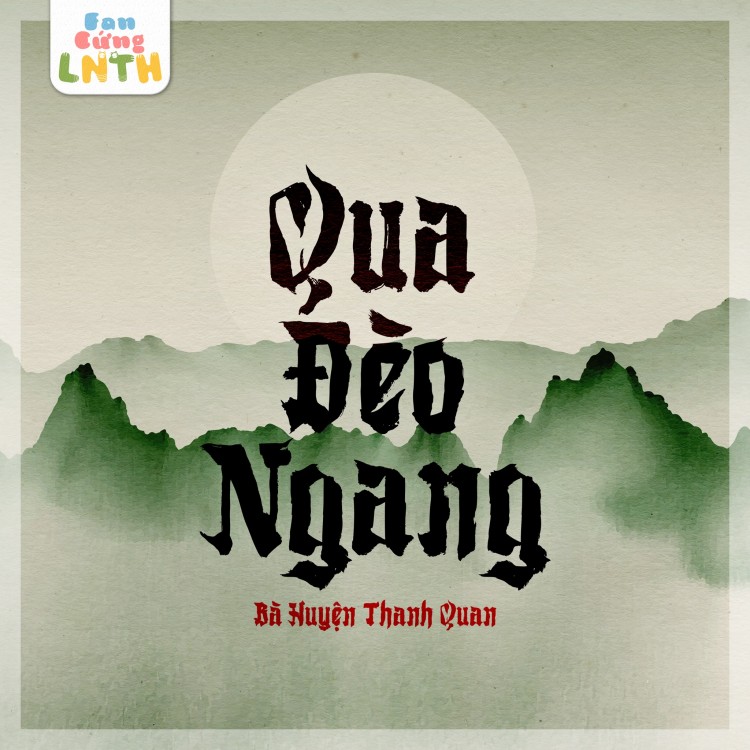
Font việt hóa LNTH Shodo Gothic – Sự kết hợp hoàn mỹ giữa thư pháp và hiện đại
Giới thiệu về Font việt hóa LNTH Shodo Gothic
Trong thế giới thiết kế đồ họa, việc lựa chọn một Font Chữ phù hợp đóng vai trò quyết định đến linh hồn của tác phẩm. Font việt hóa LNTH Shodo Gothic là một sự lựa chọn phá cách, mang đến vẻ đẹp độc đáo khi kết hợp tinh hoa của thư pháp Nhật Bản (Shodo) với cấu trúc hiện đại của phong cách Gothic. Bộ font này không chỉ giữ được những đường nét mạnh mẽ, dứt khoát mà còn đảm bảo tính thẩm mỹ cao cho người dùng Việt Nam. Nhờ quá trình việt hóa chỉn chu, các dấu câu và ký tự đặc biệt được xử lý khéo léo, giúp các bạn học sinh và thầy cô dễ dàng ứng dụng vào các dự án học tập hay trang trí bảng tin trường lớp một cách chuyên nghiệp nhất.
Đặc điểm nổi bật của bộ font LNTH Shodo Gothic
Phong cách thiết kế độc bản
Font việt hóa LNTH Shodo Gothic gây ấn tượng bởi những nét cọ mô phỏng bút lông truyền thống nhưng lại có khung xương chữ vững chãi. Sự tương phản giữa nét thanh và nét đậm tạo nên nhịp điệu thị giác lôi cuốn, phù hợp cho các tiêu đề sách, bìa báo cáo hay các mẫu slide thuyết trình cần sự trang trọng nhưng vẫn đầy tính nghệ thuật. Bộ font này giúp truyền tải thông điệp một cách mạnh mẽ và giàu cảm xúc.
Tính ứng dụng thực tế cao
Dù mang hơi hướng nghệ thuật, Font việt hóa LNTH Shodo Gothic vẫn duy trì được độ dễ đọc cần thiết. Đây là ưu điểm lớn giúp nó trở thành công cụ hỗ trợ đắc lực cho việc thiết kế poster sự kiện trường học, thiệp mời hoặc làm nổi bật các câu trích dẫn ý nghĩa. Khả năng hiển thị tốt trên cả màn hình kỹ thuật số và bản in giúp người dùng hoàn toàn yên tâm khi sử dụng.
Kết luận về Font việt hóa LNTH Shodo Gothic